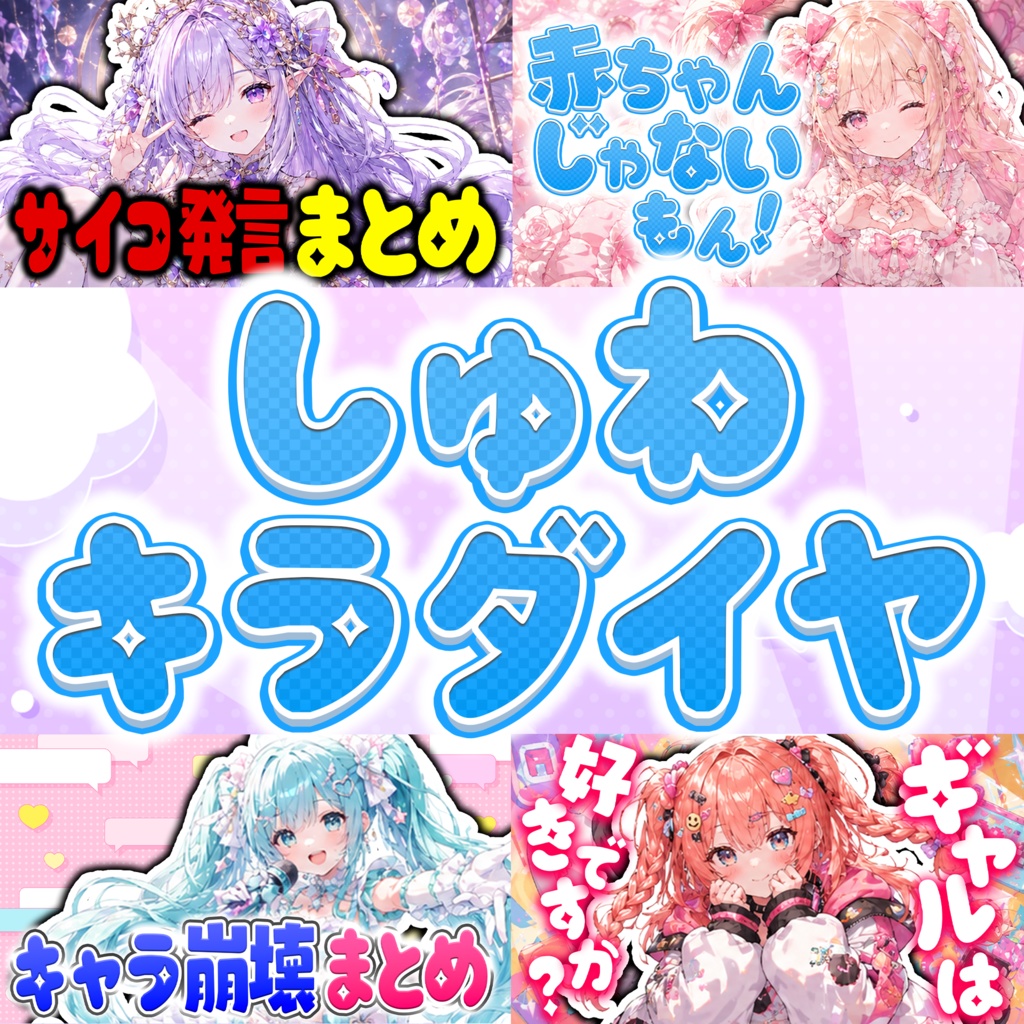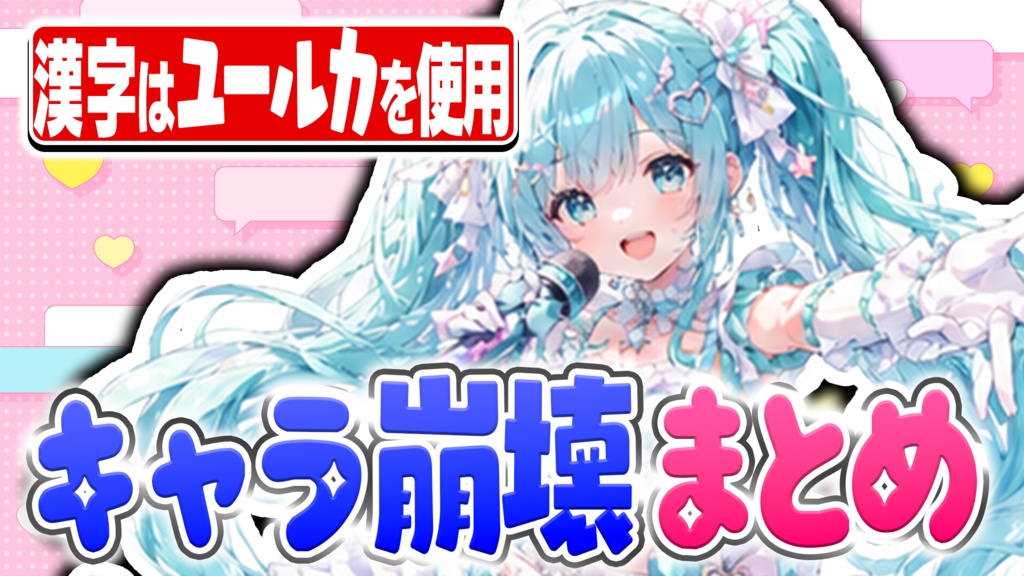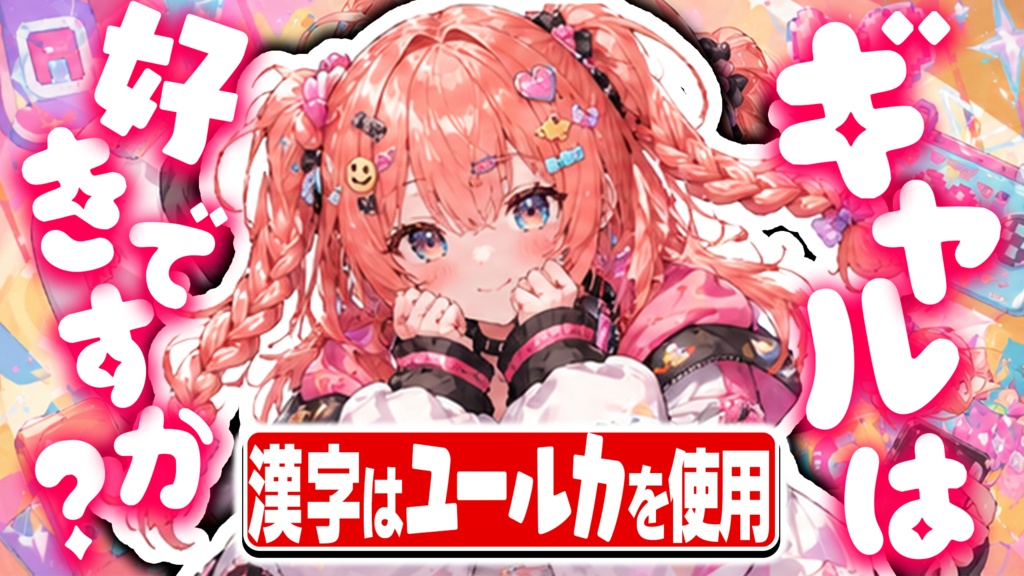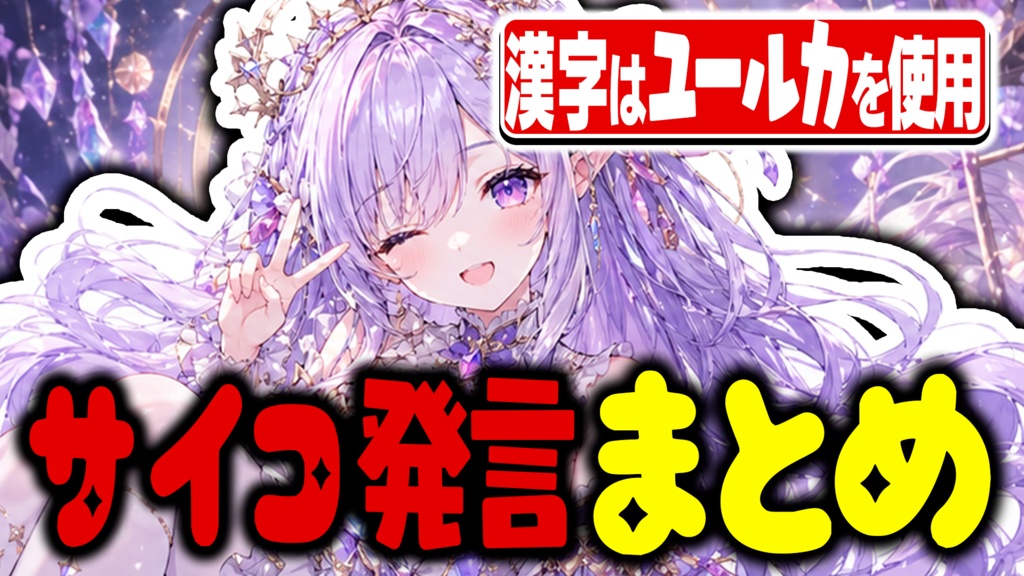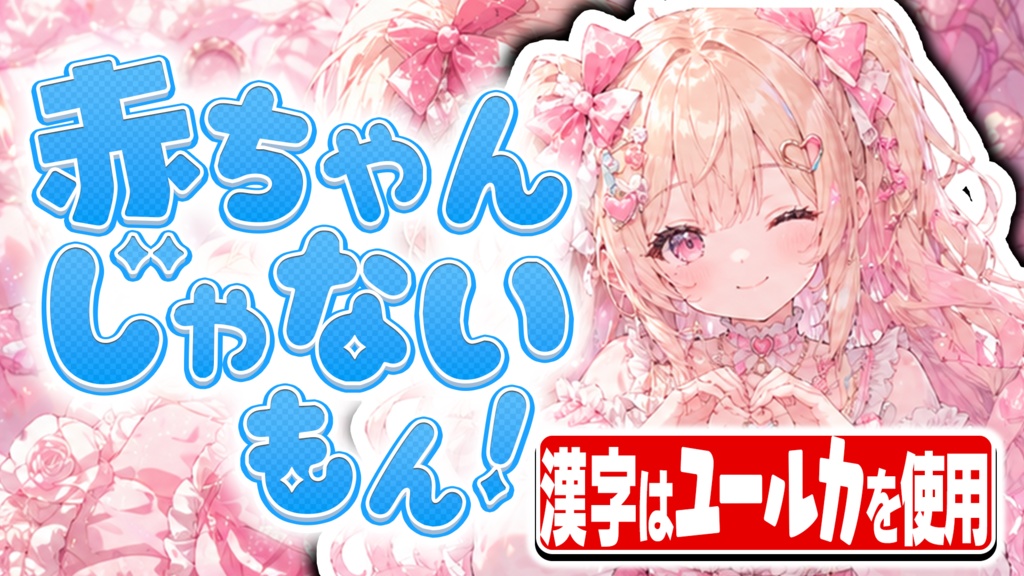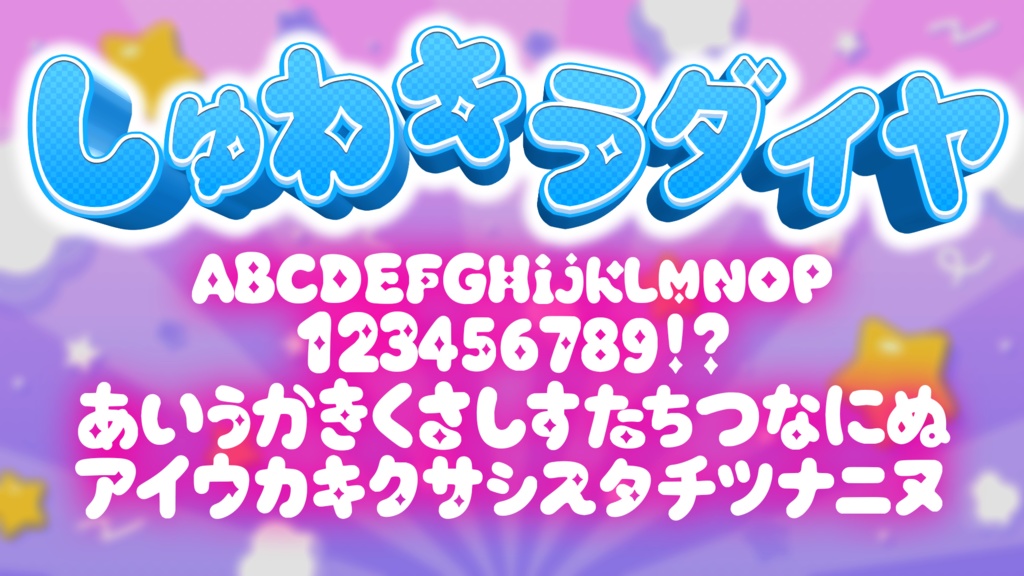
【フリーフォント】ポップで可愛い太字「しゅわキラダイヤ」【商用利用OK / VTuber・サムネ向け】
【重要】収録文字・おすすめの使い方について
本フォントはデザインに特化しているため、 【ひらがな・カタカナ・数字・大文字・小文字アルファベット・一部記号のみ】の収録となります。漢字は収録されていません。 サムネイル画像のように、漢字が含まれるフリーフォント等と組み合わせてご使用いただくと、最高に可愛く仕上がります。 【おすすめの組み合わせフォント】 ・FOT-ユールカ Std U https://lets.fontworks.co.jp/fonts/218 ・ましゅまろポップハート https://designpocket.jp/font/detail/18358